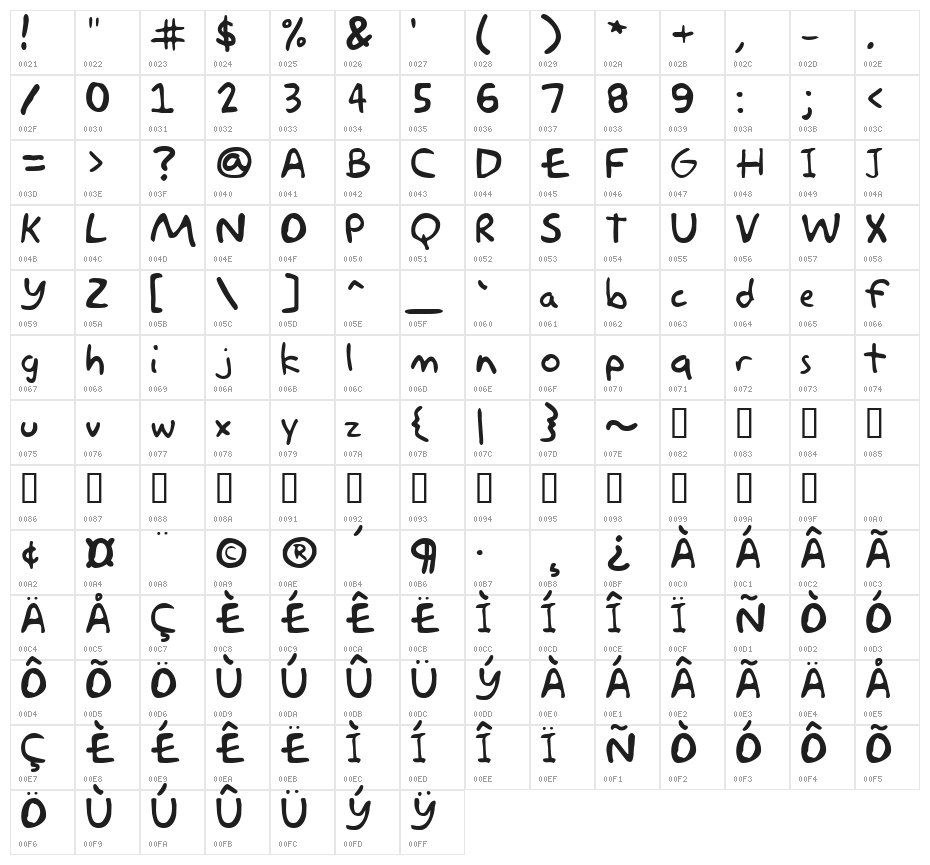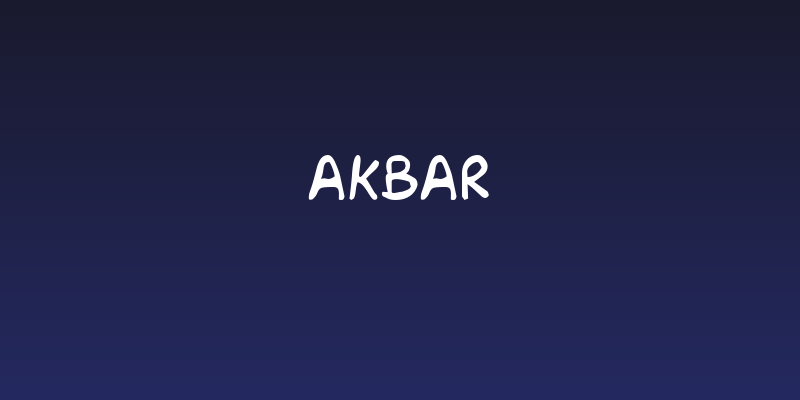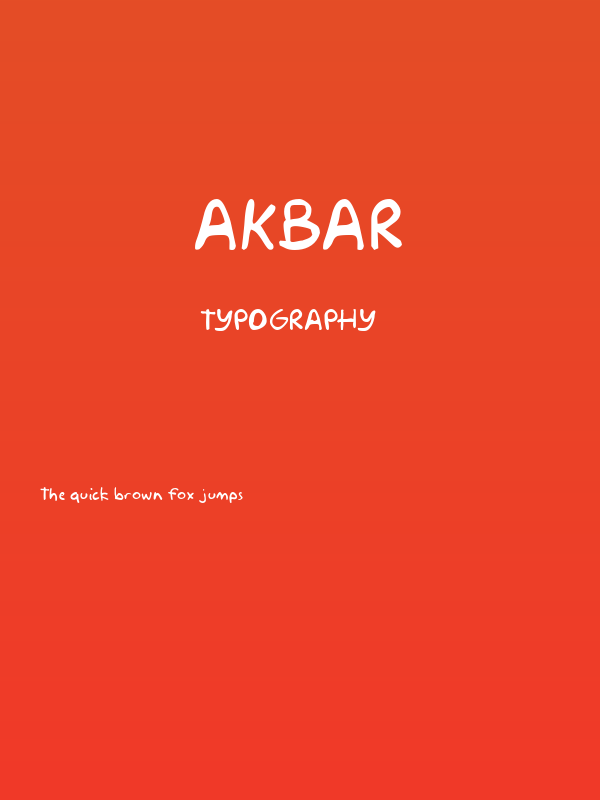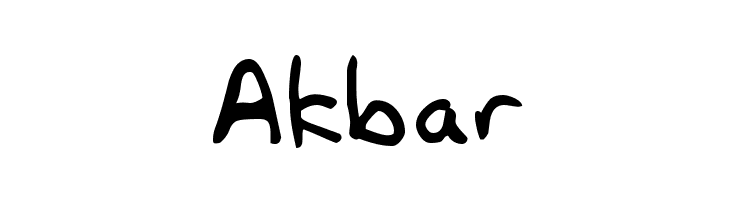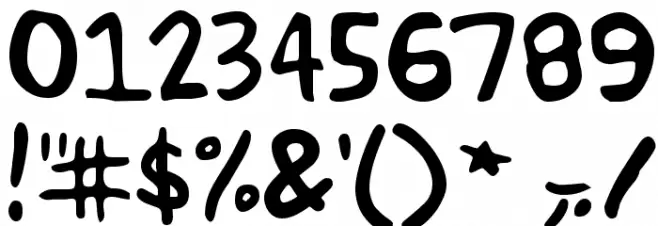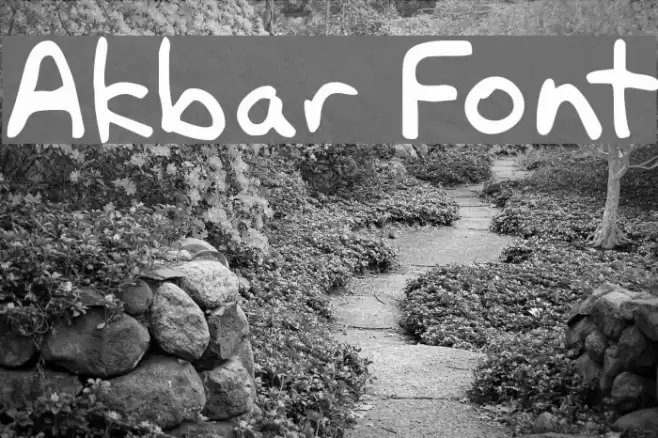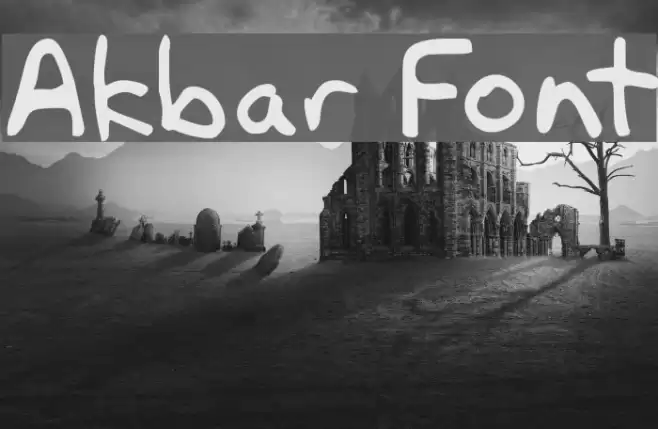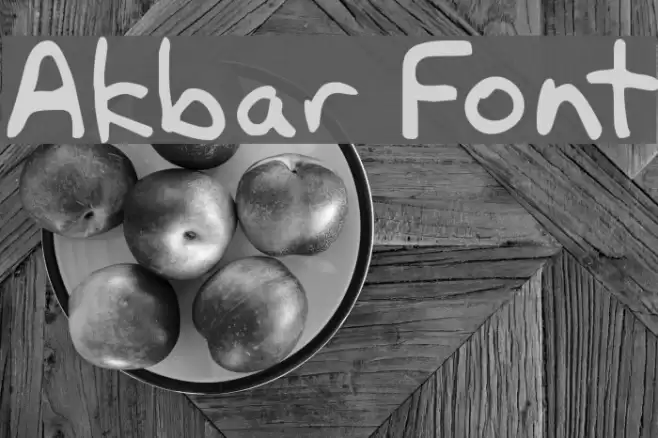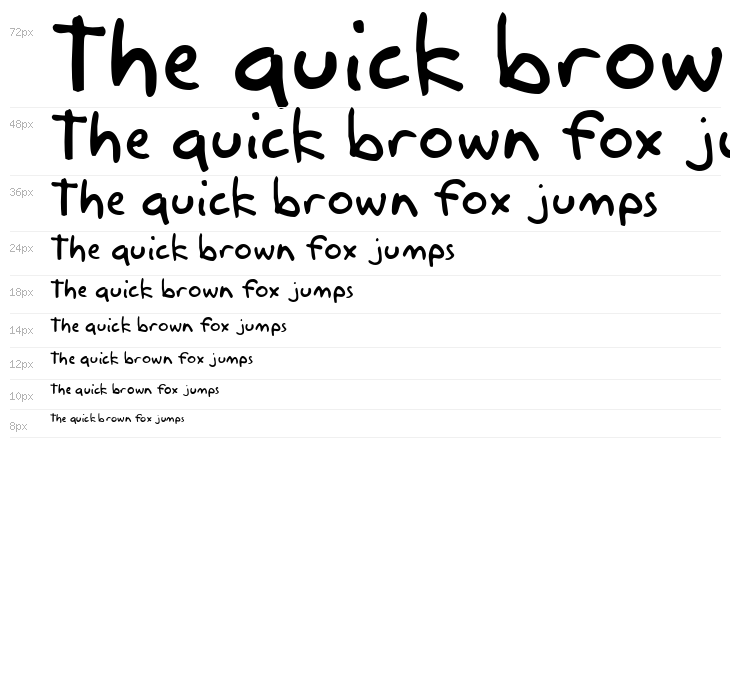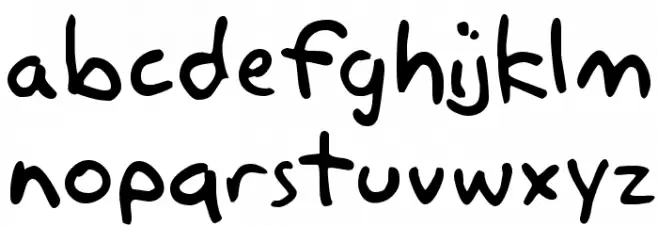
Akbar Font
| 全体的なスタイル | Casual, Playful |
| 用途 | Headlines, Logos, Informal Text |
| おすすめプロジェクト | Ideal for children's books, greeting cards, casual invitations, and playful branding. |